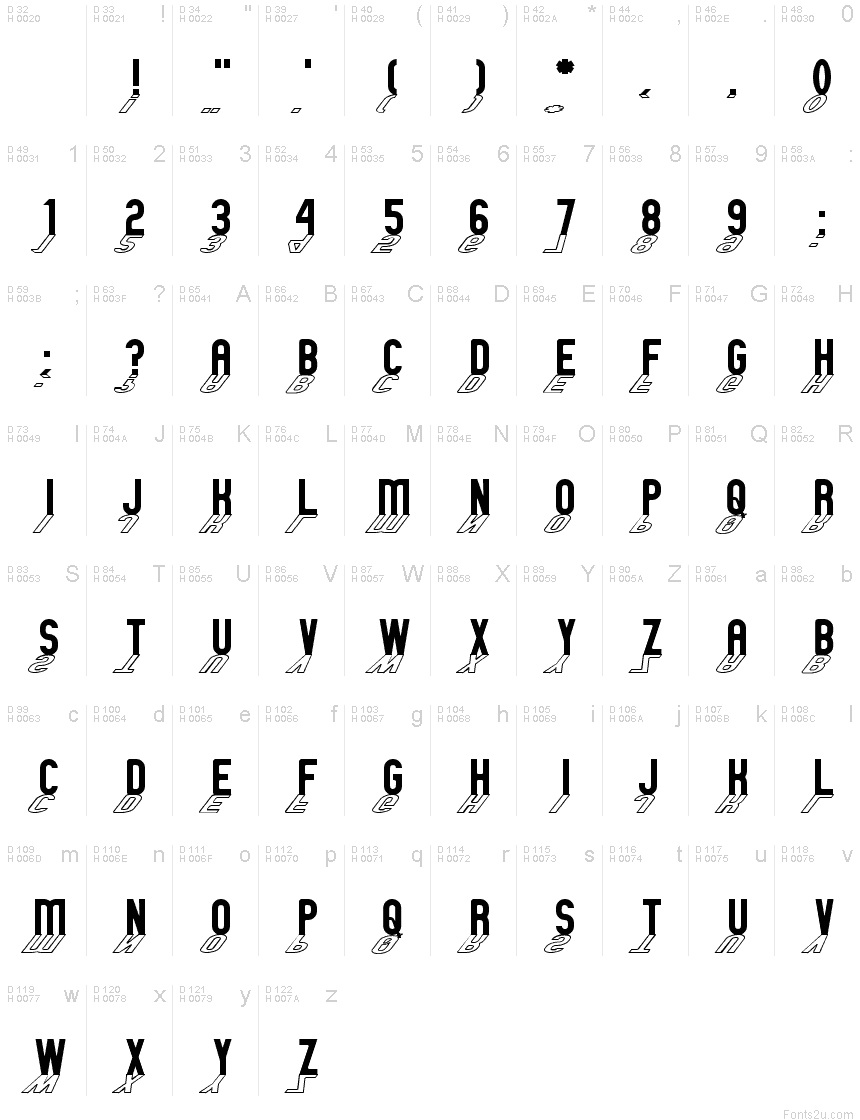
GM Exp Shadow od G.M. to darmowy, trójwymiarowy krój pisma, który wygląda, jakby został wprost zerwany z wyścigowej naklejki. Ciężkie, blokowe litery wysuwają się na pierwszy plan, podczas gdy skośna wersja z obrysem ciągnie się za nimi niczym efekt rozmycia ruchu, nadając każdemu słowu wrodzone poczucie prędkości. Wyraźne czarne wypełnienie w zestawieniu z czystym obrysem tworzy odważną, niemal mechaniczną fakturę, która natychmiast rzuca się w oczy na każdym tle, zarówno ciemnym, jak i jasnym.
Wykorzystaj GM Exp Shadow, aby dodać energii w sportowym brandingu, plakatach motoryzacyjnych i wyścigowych, tytułach gier, miejskiej odzieży, ulotkach wydarzeń czy przyciągających wzrok miniaturach na YouTube. Ten darmowy font najlepiej sprawdza się w dużych rozmiarach, gdzie jego głębia i pochylenie mogą w pełni wybrzmieć; połącz go z prostym, geometrycznym krojem bezszeryfowym w tekście głównym, aby Twoje nagłówki pozostały w centrum uwagi.
GM Exp Shadow outline